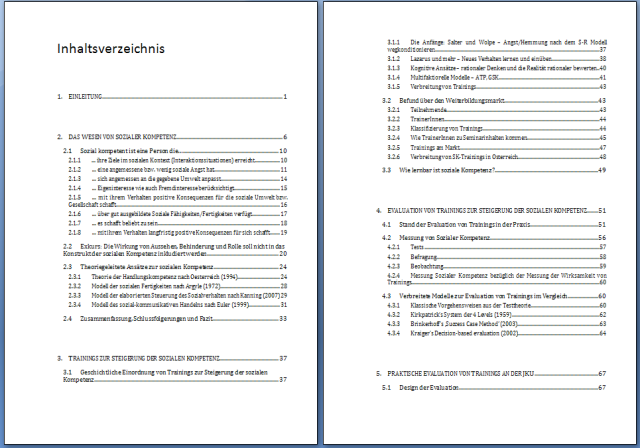
Bilder von Diplomarbeit - Kommentare gerne!
Hi!
Hier die zweite Version nachdem ich nach euren Anregungen ein paar Änderungen gemacht habe.
Das erste Inhaltsverzeichnis:
2te Version Inhaltsverzeichnis:
alle Kommentare wie immer willkommen!
[paar sachen die gemacht: silbentrennung mit 3, alle überschriften nicht-fett, shift-return bei überschriften; abstand nach tabellen auf s6 größer, abstand vor 2.2.1 und anderen größer; bei überschrift 1 abstand 72 davor, 66 danach; Hängender einzug von überschriften allen gleich, zeilenabstand: 17pt
Alte seitenränder: oben 2,5 - unten 3,5 - links 3,5 - rechts 2
Jetzt: oben 3,5 - unten 4,5 - links 3,5 - rechts 2
rechts habe ich mal 2 gelassen weil alle grafiken, seitenanzahl und kopfzeile auf dieser höhe sind]
ps ich hab gerade bemerkt dass ein paar abbildungen verschandelt sind (wohl als ich zeilenabstand geändert hab)
– Titelseite: Mir ist der Titel zu klein. Und nach wie vor würde ich es für besser halten, das Wort "Beschreibung" in die nächste Zeile zu bringen. Statt des Gedankenstrichs würde ich dann einen Punkt hinter "Kompetenz" setzen.
– Dass man hinter die letzte Gliederungsziffer keinen Punkt mehr macht, sollte Dir ein Blick in den Teil mit den amtlichen Rechtschreibregeln im Duden zeigen.
– "S." und folgende Seitennummer sollten mit geschütztem Leerzeichen gekoppelt werden. Das kannst Du mit Suchen-Ersetzen ganz schnell machen. Es darf nicht sein, dass die Nummer allein auf die nächste Zeile oder sogar Seite rutscht!
– Den Bindestrich musst Du ersetzen durch Gedankenstrich, und zwar gelegentlich im Text (z.B. Seite 5), immer zwischen "Tabelle" bzw. "Abbildung" und dem Rest der Beschriftung (auch wenn ich da den Doppelpunkt für sinnvoller halten würde – was hat ein Gedankenstrich hier verloren?), und auch immer bei der Verwendung als Aufzählungszeichen.
– Silbentrennung: Zumindest im Tabellenkopf würde ich sie ausschalten ("Be-reich" sieht nicht schön aus). Das gilt auch für die Überschriften ("wegkon-ditionieren"), wo Du das ja nur einmal in der Formatvorlage einzustellen brauchst.
– Die Kursivierung von Autorangaben müsste wohl auch in der Tabellenbeschriftung und im Abbildungsverzeichnis angewendet werden.
– Bei Abbildungen darf der Zeilenabstand nicht fest sein, sonst wird die Grafik nicht ganz dargestellt.
– Farbe: Ich würde mal ausprobieren, ob es schöner ist, die Überschriften blau zu machen und dafür die Beschriftung der Tabellen und Abbildungen schwarz. (Sinnvoller wäre es sicherlich: Wenn schon, dann müssten die Überschriften als übergeordnete Einheiten besser herausgehoben werden.)
Noch ein paar Einzelpunkte (nicht vollständig):
- Seite 2: Mir widerstrebt, dass hinter "Im Folgenden ..." kein zusätzlicher Absatzabstand kommt. Dadurch entsteht für mich als Leser der Eindruck, dass dieser Absatz und die folgende Nummer 1 zusammengehören, während die Absätze mit den Nummern 2 bis 5 mehr Abstand haben und deshalb nicht so dazugehören. Natürlich sagt mir mein Verstand dann, dass dem nicht so ist, sondern dass sich "Im Folgenden ..." auf alle Nummern von 1 bis 5 bezieht. Und so etwas finde ich eben doof. Die Typografie sollte bei solchen Textsorten die innere Ordnung des Textes sichtbar machen und ihr nicht widersprechen.
– Seite 5: Ist da eine Lücke im Text zwischen Zeile 2 und 3?
– Seite 14, Tabelle 3: Die ist immer noch in Unordnung (doppelte Zeilenlinien, unterschiedliche Formatierung der Spaltentitel).
– Seite 5: Und welchen Grund gibt es dafür, den lebenden Kolumnentitel zweizeilig zu setzen? Ach so, das ist vermutlich ein Feld und wenn die Überschrift zweizeilig ist, dann macht Word das hier auch so. Abhilfe: Den Zeilenumbruch bei der Überschrift rausnehmen und "Sozialer Kompetenz" mit geschütztem Leerzeichen zusammenhalten.
– Abbildungsverzeichnis: Die Überschrift ist kleiner als beim Literaturverzeichnis – warum? Und der hängende Einzug ist hier Quatsch, schließlich gibt es ja schon den zusätzlichen Absatzabstand. Das sollte einfach so gemacht werden wie beim Literaturverzeichnis. Die gepunkteten Linien vor den Seitenzahlen tun übrigens richtig weh! Und es sieht nicht gut aus, wenn der normale Text in den Bereich der Seitenzahlen reingeht ("Jahr").
– Müssen die Überschrift "Verwendete Literatur" und die eidesstattliche Erklärung so tief sitzen? Es gibt keinen Grund, das nicht genauso zu behandeln wie den Text auf den anderen Seiten, der ja auch immer oben beginnt.
Danke Dieter Stockert für die ausführliche Rückmeldung!
Darum folgt gleich die 3te Version - obwohl ich vieles nicht gemacht hab, aus verschiedenen gründen. Die Ausschnitte schauen auch teilweise nicht so gut aus wie die dipl weil teile von der dipl in ein neues .doc zu kopieren auch nie so 100% passt. (überschrift 2 ist in meinem original zb einzeilig)
Fragen/Kommentare:
- Wie kann Ich verhindern dass eine Tabelle über 2 Seiten geht? Bei Absatz 'Diesen Absatz zusammenhalten' (wenn ich ganze Tabelle markiere) hilft mal nicht.
- word hat alle meine Abbildungen irgendwie verdeckt. Textumbruch ist wohl auf 'mit Text in Zeile' gestellt (was heißt dass?), aber ich stelle es auf 'oben und unten' und richte es neu ein notwendigerweise. Generell spielen die Abbildungen etwas verrückt wenn es Änderungen auf der Seite gibt. Naja.
- dass mit der 2stelligen Kopfzeile bei Kapitel 3: aah, drum ist das! super, mit dieser Info konnte ich das problem lösen.
die ersten paar seiten:
word07: http://www.steekr.com/n/50-17/share/LNK32954a6433cd7e7a5/
pdf: http://www.steekr.com/n/50-17/share/LNK10904a6433f4dd632/
lg! mike
Wie ich es möchte?
Jawohl, wie Du es möchtest! Ich habe schon mehrfach darauf hingewiesen, daß sich auch andere Programme, darunter InDesign, OpenOffice Writer, Scribus, Ragtime etc. sehr ähnlich verhalten, was die Silbentrennung angeht. Darauf bist Du bisher noch nie eingegangen. Und eine Alternative (außer vielleicht Calamus) zu Word, die genau das macht, was Du möchtest, hast Du auch noch nicht vorgeschlagen. Und Du scheinst auch immer wieder gerne zu »vergessen«, daß Deine Anschuldigungen von Word-Versionen herrühren, die bereits 10 Jahre alt sind. Wir haben das alles schon gehabt: Seit Word2003 reagiert die Silbentrennung ganz einwandfrei auf Trennungen, die durch den Benutzer eingegeben werden! Trennt Word »Wirbelsäu-le« und ich füge einen bedingten Trennstrich nach »Wirbel« ein, dann trennt Word auch dort! Was soll denn das, daß Du das einfach selektiv immer wieder vergißt? Ich kann mir auch aus einem Forum einen 10 Jahre alten Calamus-Bug raussuchen und den hier immer wieder vorbringen. Was aber soll das bringen?
Dass CRudolph und ich ihr eine ordentliche Portion Praxistauglichkeit attestieren, berührt dich überhaupt nicht
Es verwundert mich. Es zeigt mir aber auch, dass die Erwartungen an Praxistauglichkeit offensichtlich recht unterschiedlich sein können. Meine Kritik an der Silbentrennung von Word kam schließlich nicht von ungefähr, sondern erwuchs aus meiner Praxis.
Es sind ja nicht nur wir, die Praxistauglichkeit attestieren, es sind sehr viele Nutzer und Deine Kritik an der Silbentrennung in Word ist veraltet. Wir alle schätzen Deine Meinung hier im Forum sehr, aber sowas kratzt einfach an der Glaubwürdigkeit.
- Wie kann Ich verhindern dass eine Tabelle über 2 Seiten geht? Bei Absatz 'Diesen Absatz zusammenhalten' (wenn ich ganze Tabelle markiere) hilft mal nicht.
Ich gehe davon aus, daß es nur eine oder zwei Zeilen sind, die umgebrochen werden? Wenn der Platz nicht reicht, dann reicht er eben nicht, da hilft auch kein »Diesen Absatz zusammenhalten«. Wenn Du für die Tabelle ein eigenes Format angelegt hast mußt Du nur minimal an den Parametern spielen (Zeilenabstand) damit es wieder paßt. Alternative könntest Du »Section breaks« einfügen und das Format der speziellen Seite etwas anpassen. Das wird aber auf Dauer mehr Ärger als Freude bereiten. Im Übrigen sollten seitenlange Tabellen eigentlich nur in Ausnahmefällen im Fließtext auftauchen. Lange tabellarische Auflistungen gehören normalerweise in den Anhang.
- word hat alle meine Abbildungen irgendwie verdeckt. Textumbruch ist wohl auf 'mit Text in Zeile' gestellt (was heißt dass?), aber ich stelle es auf 'oben und unten' und richte es neu ein notwendigerweise. Generell spielen die Abbildungen etwas verrückt wenn es Änderungen auf der Seite gibt. Naja.
Wie fügst Du Abbildungen ein? Die mit Abstand sicherste Variante ist das Einfügen als »In line with text«, wobei der Zeilenabstand nicht als »genau« definiert sein darf, sonst schneidet Dir Word das Bild auf Zeilenabstandshöhe ab. Selbst wenn es am Ende anders aussehen soll: Füge die Abbildungen erstmal so ein und kümmere Dich um alles Weitere ganz am Ende, wenn der Text steht. Abbildungen, und hier muß man die von Dieter angesprochene Praxistauglichkeit von Word (aber auch von OpenOffice Writer) wirklich in Frage stellen, sind immer schon ein Schmerz im Gesäß gewesen.
Was das pdf angeht:
Warum sind die Bildunterschriften im Mittelsatz? Blocksatz oder linksbündiger Flattersatz sind besser geeignet.
Bei den Überschriften ist die 2. Zeile nicht an der ersten ausgerichtet. »Kompetenz« steht nicht unter »Das«.
Word erlaubt zwar nur automatische Verzeichnisse in einem etwas limiterten Umfang, auch daran läßt sich aber schrauben. So ist es nicht sonderlich ansprechend. Ich zeige bei Gelgenheit mal andere Beispiele.
Hast Du viel Literatur? Im Literaturverzeichnis würde ich empfehlen keine Abstände zwischen den Einträgen zu machen und die Erstautoren mit Auszug zu setzen. Etwas kleiner als der Fließtext darf es auch sein, das spart ggf. sehr viel Platz und macht es trotzdem nicht unübersichtlicher.
All diese Fragen werden übrigens hier mit einigen informativen Beispielen abgehandelt, für jeden Diplomanden eine wirklich lohnende Investition!
Ich beziehe mich auf Version 3:
Die Ränder sind nicht einheitlich; die Seitenzahl ist nicht auf allen Seiten an der gleichen Stelle. Den Strich davor würde ich weglassen.
Die Schriften waren vorher besser (Cambria für den Haupttext). Du könntest für Überschriften mal die Corbel dazu probieren.
Dieters Idee, die Überschriften blau zu setzen, finde ich gut. Ich würde aber ein dunkleres Blau verwenden als das, worin Du jetzt die Abbildungsbeschriftungen gesetzt hast.
Verstehe ich richtig, daß Du den Rand rechts so klein lassen willst, weil sonst die Tabellen und Abbildungen nicht mehr rein passen? Notfalls würde ich diese dann einfach in den Rand ragen lassen; sinnvoller wäre aber, sie zu überarbeiten.
Hi!
- Tabelle geht über 2 Seiten: Ich hätte gern dass eine kleine Tabelle, anstatt dass sie in der Mitte geteilt wird, auf die nächste Seite verschoben wird. Sonst halt von Hand am Schluß.
Dank euch, ich mach jetzt mal ein bisschen Urlaub :)
Sonst halt von Hand am Schluß.
Genau so. Kümmere Dich um diese spezifischen Layout-Fragen im Moment einfach nicht. Es kommt garantiert auf einmal noch Text vor der Tabelle dazu oder wird gestrichen und schon sieht schon wieder alles ganz anders aus. Meiner Erfahrung nach verplempern die Leute unendlich viel Zeit mit solchen Schönheitskorrekturen, die dann nach jeder Korrektur immer wieder neu gemacht werden müssen. Einfach ignorieren. Oder gleich mit LaTeX arbeiten, da kommt man gar nicht erst in Versuchung.
Später ist es dann relativ egal: Abbildungen und Tabellen müssen in wissenschaftlichen Texten sowieso immer im Text explizit genannt werden, dann kann man sie problemlos auch einfach so auf die nächste Seite verschieben daß man keine Probleme hat.
Schönen Urlaub,
die häßliche, wenngleich mit Einführung der neuen Rechtschreibung erlaubte Silbentrennung mit nur einem einzigen Buchstaben am Zeilenende ("Ü-bersetzung")
stimmt nicht. worttrennung hinter einem einzelnen vokal sieht die aktuelle fassung der rechtschreibregeln nicht (mehr) vor. keine ›a|bendlichen ü|bersetzungen‹.
Ich habe schon mehrfach darauf hingewiesen, daß sich auch andere Programme, darunter InDesign, OpenOffice Writer, Scribus, Ragtime etc. sehr ähnlich verhalten, was die Silbentrennung angeht. Darauf bist Du bisher noch nie eingegangen.
Sollte mir das entgangen sein? Ich kann mich nicht erinnern, das gelesen zu haben. Aber egal welches Programm: Wenn ich die Silbentrennung ausschalte, dann hat auch verdammt noch mal die Silbentrennung ausgeschaltet zu sein.
Und eine Alternative (außer vielleicht Calamus) zu Word, die genau das macht, was Du möchtest, hast Du auch noch nicht vorgeschlagen.
Äh, das hat schon Signum! selig auf dem Atari richtig gemacht. Dass ich Calamus in Bezug auf die Silbentrennung ins Spiel gebracht hätte, kann ich mir gar nicht mehr denken. Das würde auch gar nicht gut passen, dazu ist die Philosophie zu unterschiedlich.
Und Du scheinst auch immer wieder gerne zu »vergessen«, daß Deine Anschuldigungen von Word-Versionen herrühren, die bereits 10 Jahre alt sind. Wir haben das alles schon gehabt: Seit Word2003 reagiert die Silbentrennung ganz einwandfrei auf Trennungen, die durch den Benutzer eingegeben werden! Trennt Word »Wirbelsäu-le« und ich füge einen bedingten Trennstrich nach »Wirbel« ein, dann trennt Word auch dort!
Wir haben seit einem Jahr Word 2003 im Büro und ich habe das heute mal ausprobiert: Stimmt. Diesen Kritikpunkt werde ich also in Zukunft weglassen. Dass das aber seit Word 2003 besser ist, das stand so explizit hier noch nicht. Irgendwo (hier oder in der Word-Newsgroup?) habe ich mal etwas gelesen und neulich dann erst noch einmal nachgesehen, aber da war mir die Formulierung zu unklar, sodass ich das nicht übernehmen wollte.
Was soll denn das, daß Du das einfach selektiv immer wieder vergißt?
Arno Schmidt hat sich ja seines gusseisernen Gedächtnisses gerühmt. Meines ist aus Plastik und wie ein Sieb noch dazu.